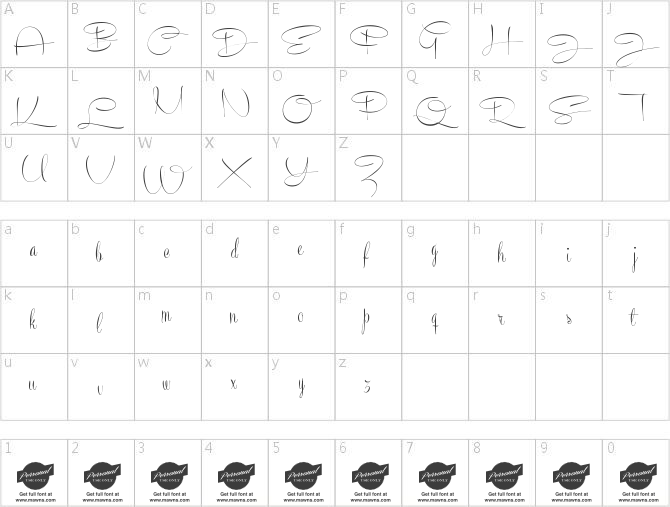
Recorda Script Personal Use Onl 詳情頁
Recorda Script Personal Use Onl字體字庫是一款讓人賞心悅目、百看不厭的英文字體,適合各類廣告和產(chǎn)品包裝設(shè)計(jì)應(yīng)用,字體大小0.23MB,格式為ttf字體,上傳用戶是小北,作者/版權(quán)方為未知